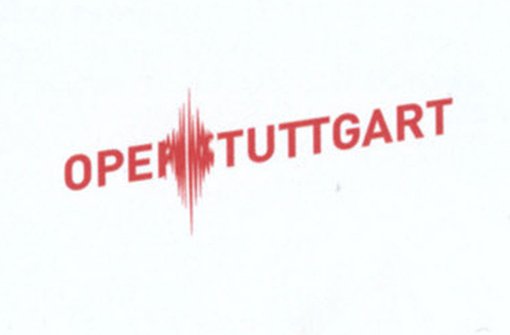
Ja, das könnte sein. Oder die Bauarbeiten von Stuttgart21 haben den Grafiker erschüttert. :-o
Oh … vielleicht ein kleines Erdbeben während der Gestaltung? :-?
Kathrin, Du hast den Gestalter verstanden:
Wenn man an Erdbeben denke, sagt der Surface-Chef Markus Weisbeck, habe er "kein Problem damit". Die "dynamische Notation" sei durchaus erwünscht.
Auch bemerkenswert:
Seinen vollen Charme entfalte das Logo indes erst, wenn es animiert mit wandernden Amplituden zu sehen sei, verheißt Weisbeck - etwa auf geplanten Spots in der U-Bahn.
Seinen vollen Charme entfalte das Logo indes erst, wenn es animiert mit wandernden Amplituden zu sehen sei, verheißt Weisbeck – etwa auf geplanten Spots in der U-Bahn.
Ach. Da wird ein Logo gestaltet, das nur in Ausnahmefällen seinen Charme entfaltet? Wie interessant.
Wenn ich da an große Designagenturen denke und an die Menge von Leuten, die auf einem solchen Projekt arbeiten (zumindest zu Beginn, bei der Ideenfindung) und die Stundensätze, die da veranschlagt werden, dann ist der fünfstellige Betrag relativ schnell erreicht.
Grundsätzlich finde ich die Idee mit der Amplitude nicht verkehrt, auf die Idee kann man beim Brainstorming schon kommen. Allein: die Umsetzung gefällt mir nicht. Es wirkt ein bisschen wie eine Herzkurve auf dem Monitor, bei der auf den großen Schlag die Nulllinie folgt. Ich kann mir sehr gut vorstellen, dass die Sache als Animation hervorragend funktioniert – vermutlich ist diese dann auch mit passender akustischer Begleitung versehen. Aber es klappt für mein Empfinden nur sehr bedingt, eine solche Logoidee primär von der Animation aus zu denken und dann auf die Zweidimensionale reduziert zurück in die Printwelt zu spiegeln. Zumal der interessierte Betrachter dem Logo wesentlich häufiger in der gedruckten als in der animierten Form begegnen wird (Plakate, Veranstaltungskalender, Zeitung, Programmheft, etc.). Das Logo in der Form, wie bertel sie hier zeigt, überzeugt mich jedenfalls nicht. :-)
Ich kenne die Agentur nicht, die das Logo entwickelt hat. Weiß einer von Euch, ob die primär aus dem Screendesign- und Animationsbereich kommen?
Nein, die Agentur ist für Arbeiten aus den Bereichen Markenentwicklung, Kultur und Ausstellungsdesign bekannt. Und so eine Luftnummer ist man eigentlich von denen nicht gewohnt.
An Oper erinnert mich dieses Logo auf jeden Fall nicht.
Was wollen die bloß rüberbringen?! :-?
Wir wissen natürlich nicht, wie dieses Logo entstanden ist und wie der Entwicklungsprozess vonstatten ging. Logoentwicklungen können manchmal unglücklich verlaufen – vielleicht hatte die Agentur einen ganz anderen Favoriten, aber der Kunde bestand auf dieser Ausführung? Ich will keine Agenturenschelte betreiben, für eine faire Beurteilung müsste man Genaueres wissen.
… Ich will keine Agenturenschelte betreiben …
Ich auch nicht. Aber Logoschelte will ich schon betreiben ;-)
für eine faire Beurteilung müsste man Genaueres wissen.
Auf den von Stefan verlinkten Thread gibts schon interessante Infos dazu.
Also, ich habe jetzt in den von Stefan verlinkten Fontblog geschaut. Da bekommt man zwar einige Hintergründe für die dreigeteilte Gestaltungsaufgabe der Stuttgarter Bühnen geliefert, aber was genau bei der Gestaltung des hier besprochenen Logos abgelaufen ist, wird dort nicht preisgegeben. Wie auch – so ein Gestaltungsprozess ist ja in der Regel ein vertraulicher Vorgang und weder Agentur noch Kunde werden ohne Not Interna nach außen tragen. Verständlich.
Wieso lesen eigentlich immer alle »OPEN« und nicht »OPEL«? Als wildgewordener Opelblitz würde das Ding doch glatt durchgehen und für ein Autohaus wäre der Auftritt doch auch irgendwie akzeptabel.